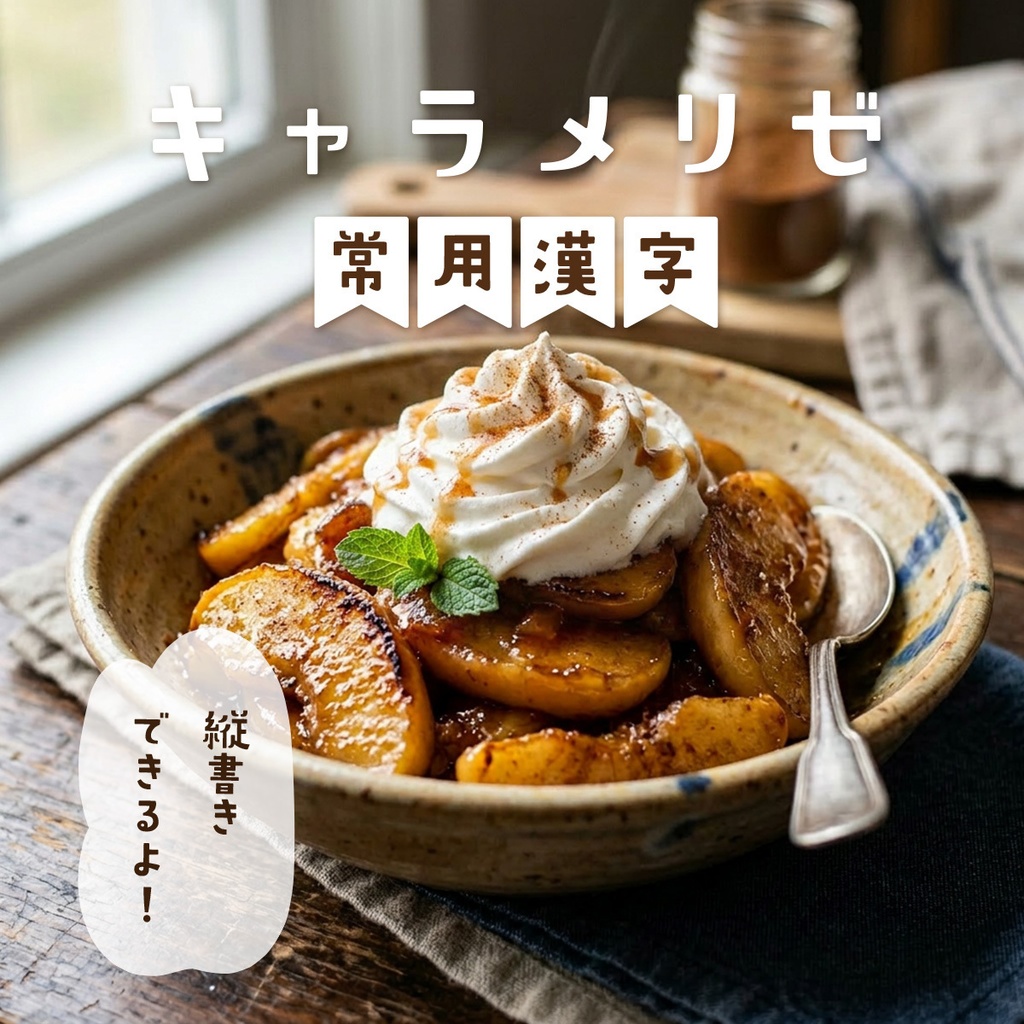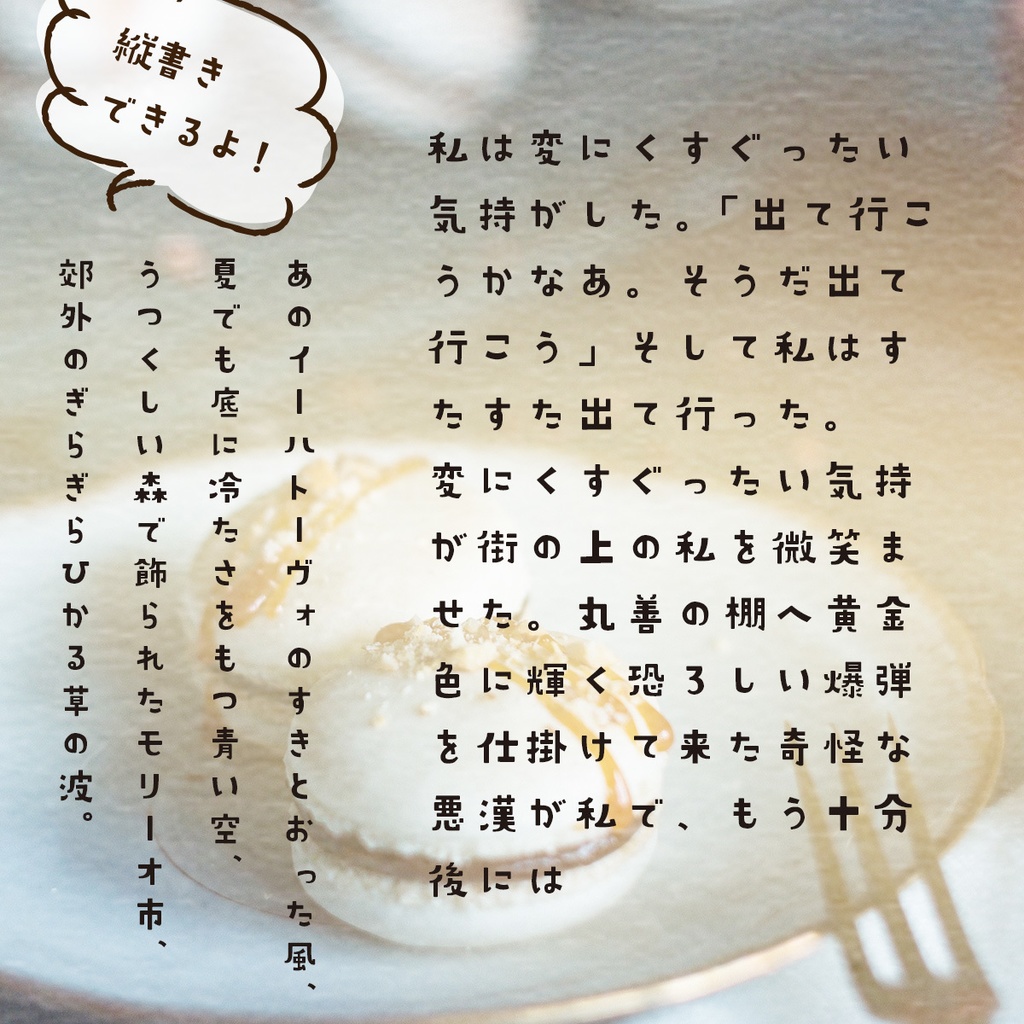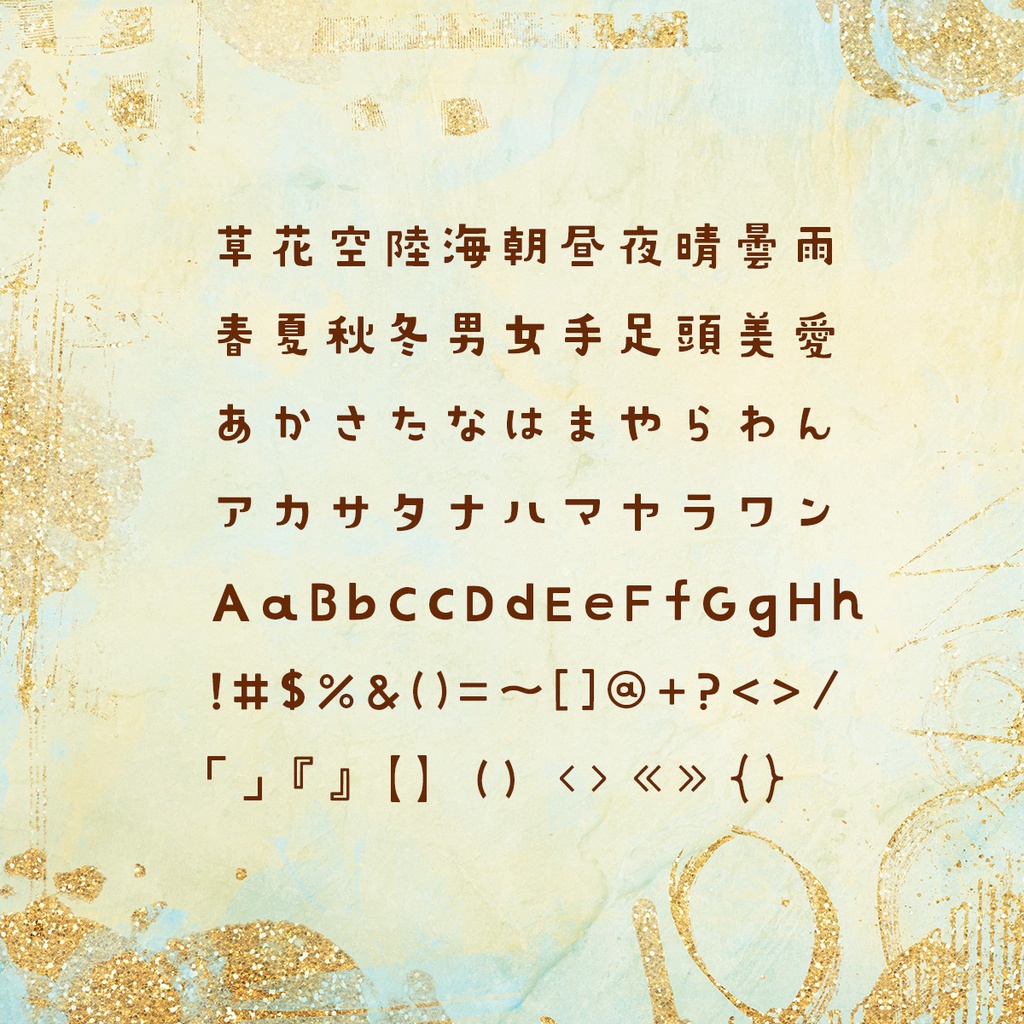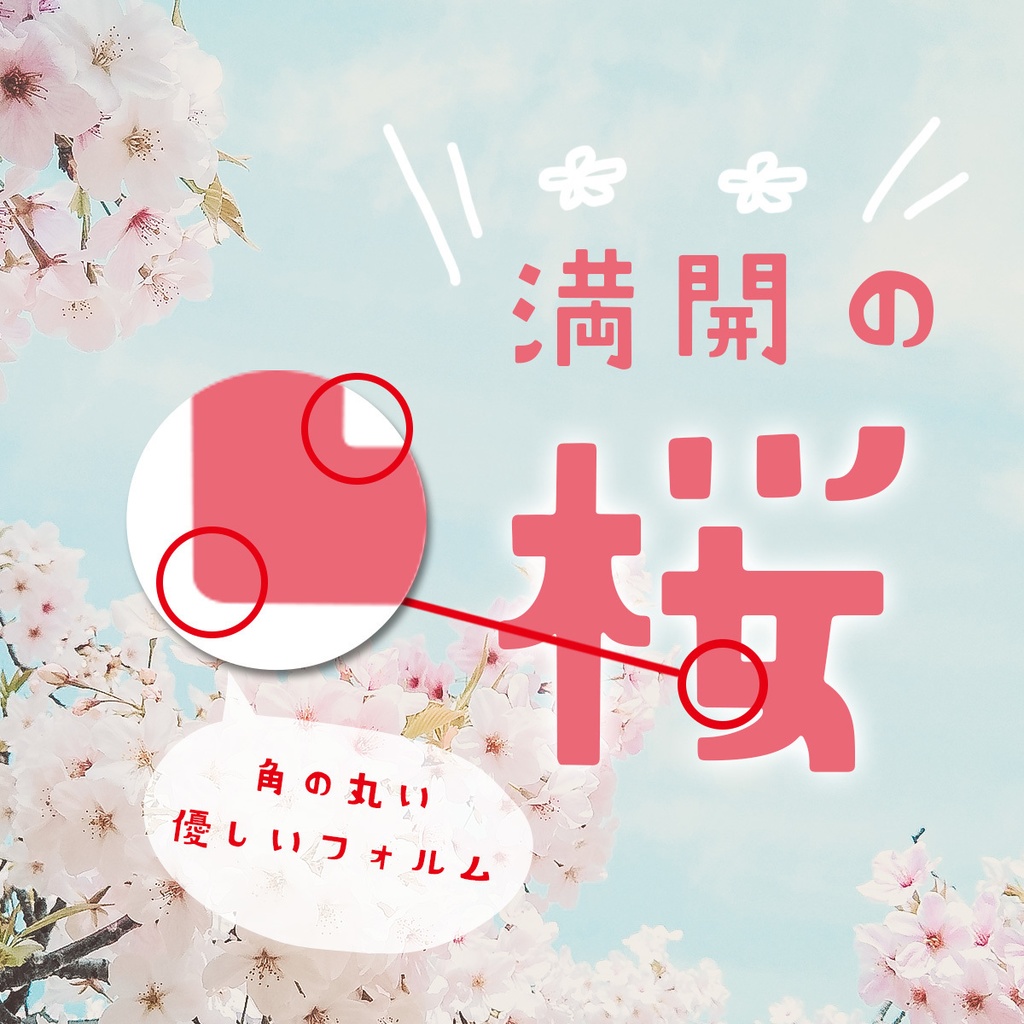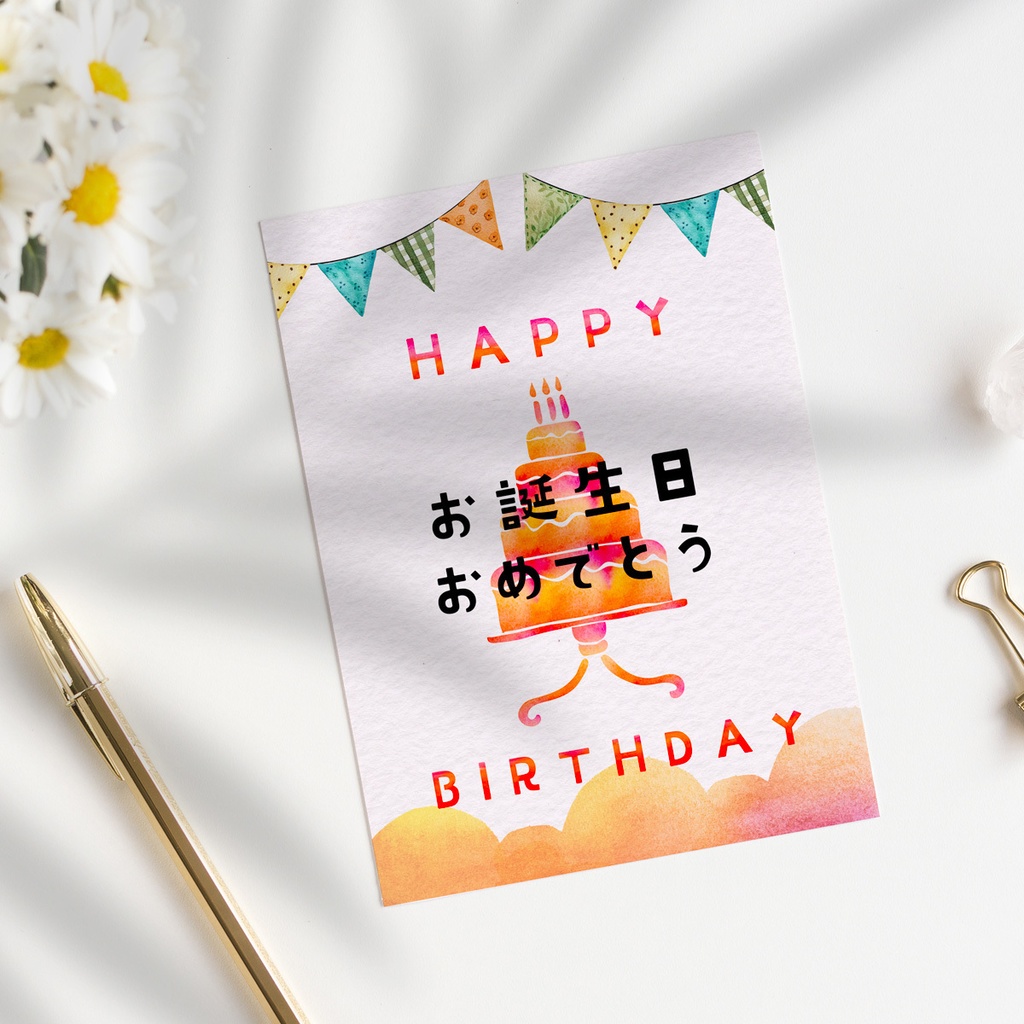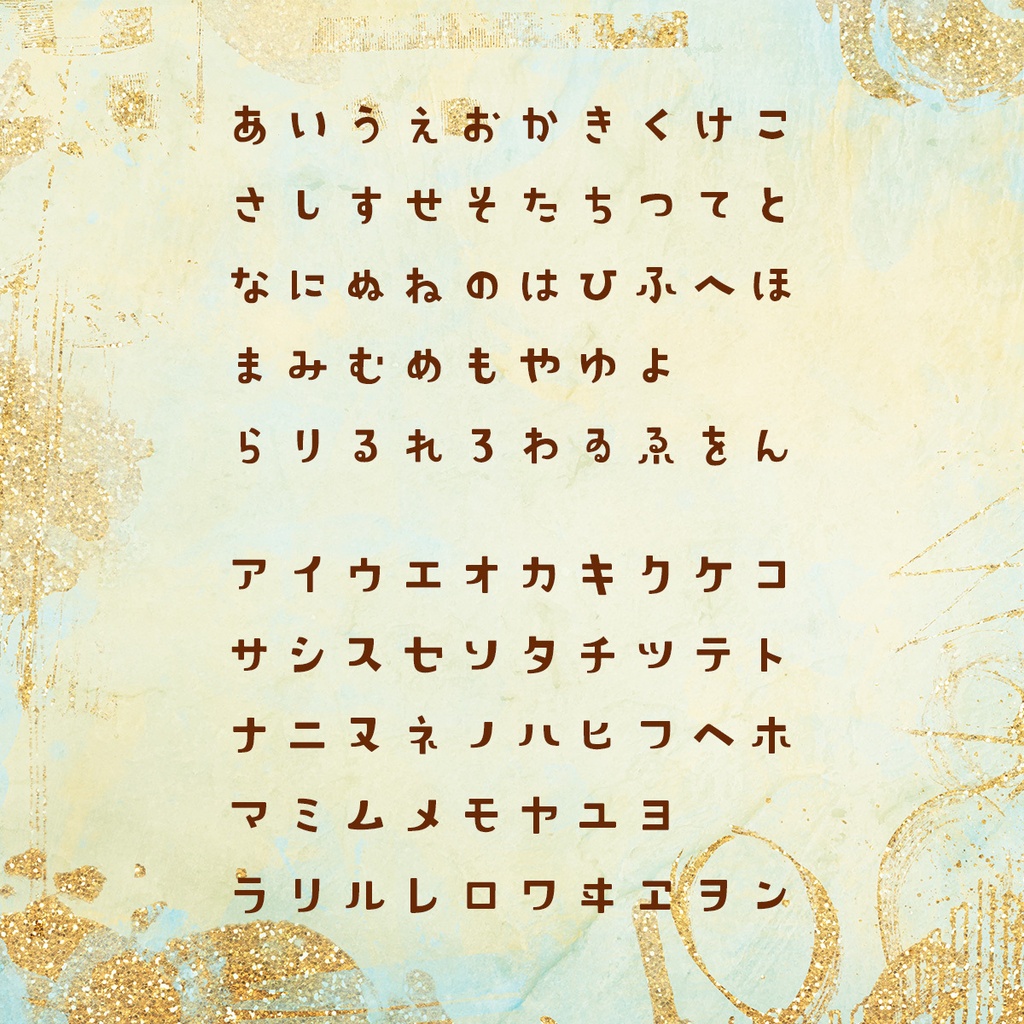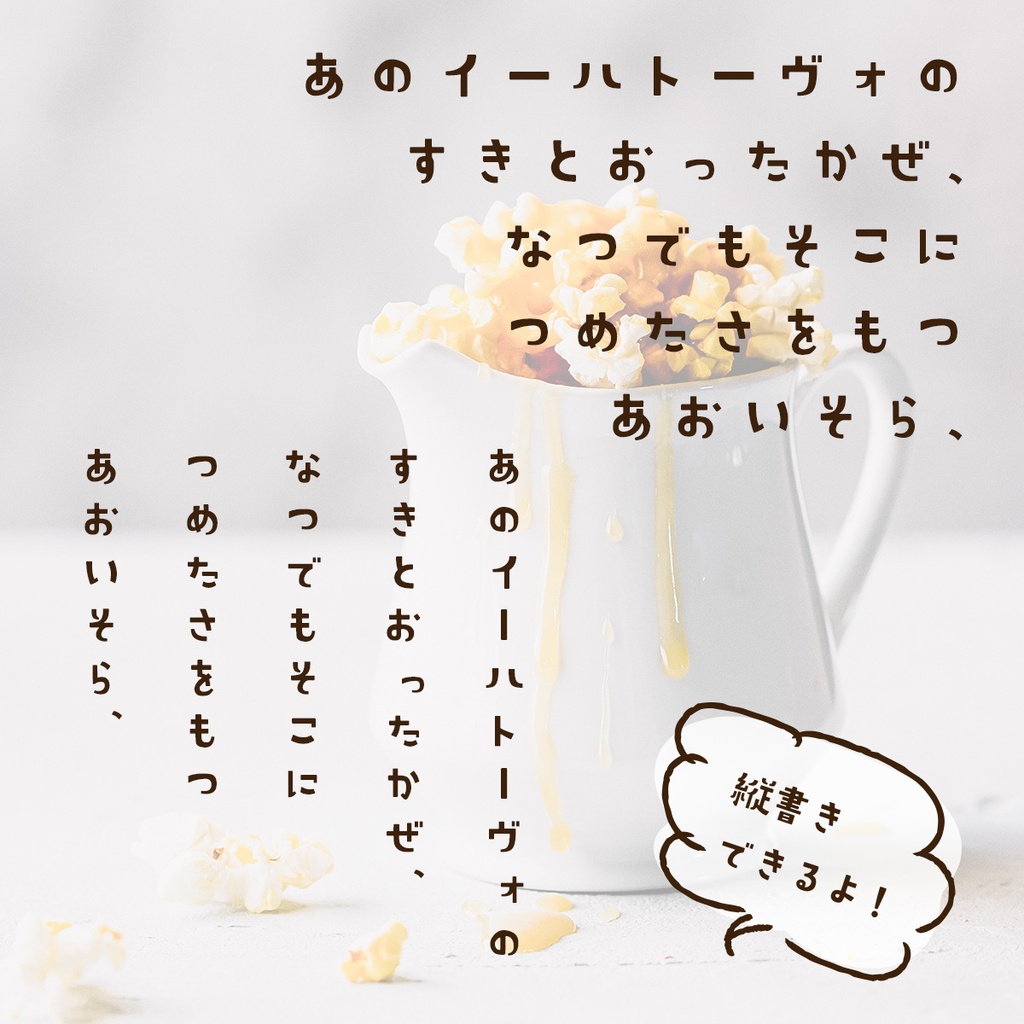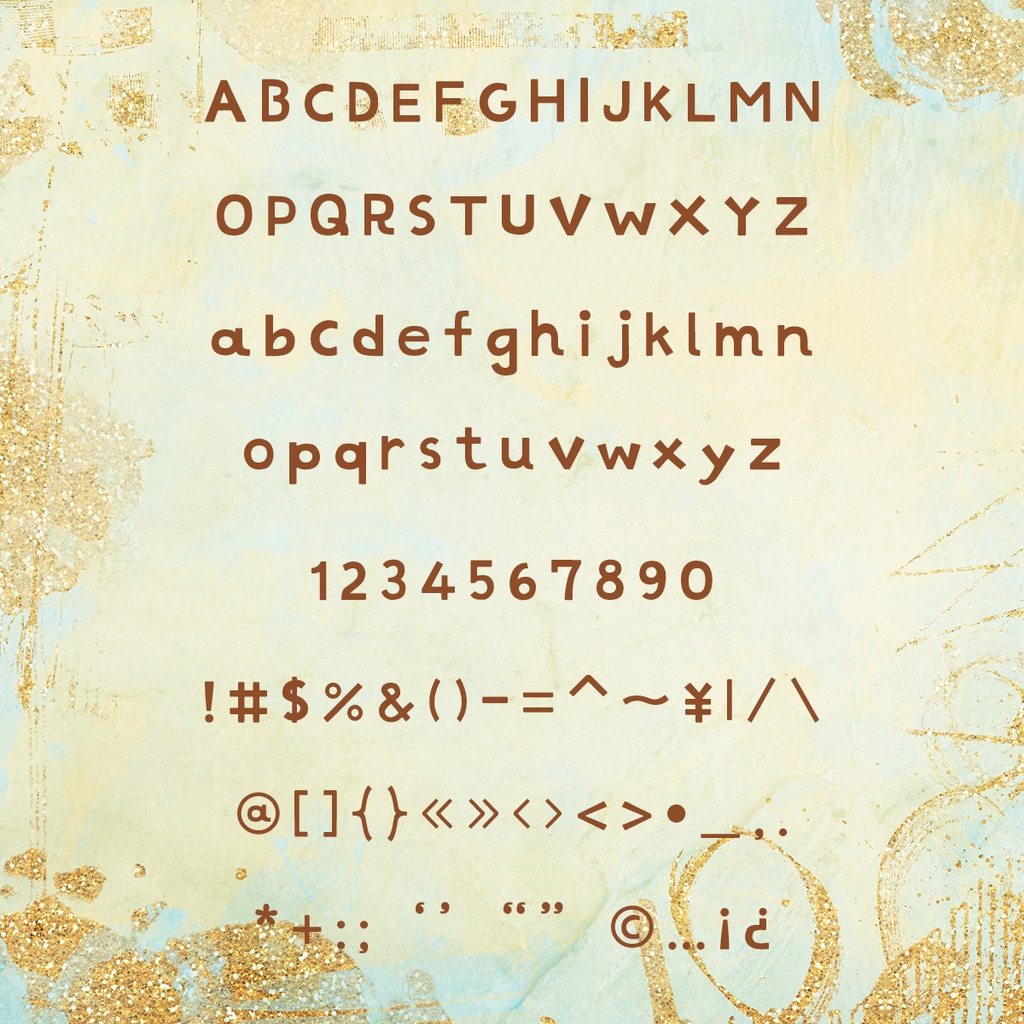
【商用可/縦書き対応】キャラメリゼ フォント|丸みかわいい日本語フォント 常用漢字・ひらがな・カタカナ CARAMELIZE
【常用漢字・ひらがな・カタカナ】CARAMELIZE | キャラメリゼ フォント
【商用可・縦書き対応】常用漢字2136字+ひらがな・カタカナ・アルファベット・記号を収録した、丸みのかわいい日本語フォントです。 同人誌・SNS・動画・WEBデザインなど幅広い用途にお使いいただけます。 どの角も丸みをおびたやさしいフォルムが特徴です。 商用利用OKです。 常用漢字・ひらがな・カタカナ・アルファベット・記号 収録 フォント形式:OpenTypeフォント 【動作環境】Windows / Mac 対応 【インストール方法】 Windows:ダウンロードしたZIPを解凍し、.otfファイルを右クリック→「インストール」 Mac:Font Bookにファイルをドラッグ&ドロップ ▼ まず試してみたい方へ ・無料お試し版(英数字・記号のみ)→ https://vanillabeanz.booth.pm/items/2783311 ・ひらがな・カタカナ版(¥390)→ https://vanillabeanz.booth.pm/items/2783329